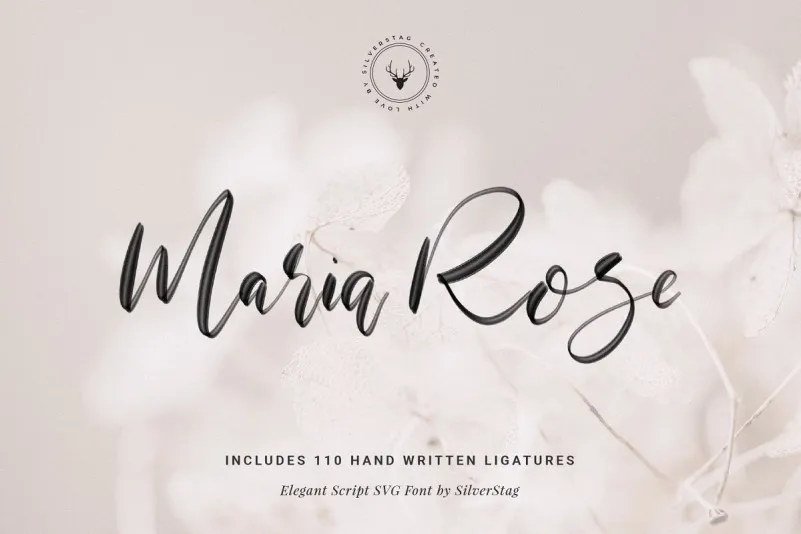
Maria Rose SVG Script Font – Download Grátis
A Maria Rose SVG Script Font é uma nova escolha para aqueles que buscam um estilo elegante e sofisticado. Desenhada para ser versátil, ela pode destacar-se ou complementar maravilhosamente qualquer tipo de letra sans serif ou romana. Esta fonte script vem com uma textura realista de traços a mão em cores pastel e água. É perfeitamente adaptável a um amplo espectro de projetos gráficos, desde logomarcas femininos até cartões de casamento, cabeçalhos para mídias sociais, embalagens de produto e muito mais. Ideal tanto para designers profissionais quanto para amadores que procuram uma fonte elegante, a Maria Rose SVG Script Font oferece um toque delicado e único capaz de dar vida aos seus projetos. Seja você criando material para o seu negócio ou apenas adicionando um toque especial a mensagens pessoais, esta fonte é perfeita para complementar suas ideias com um estilo atemporal e sofisticado.